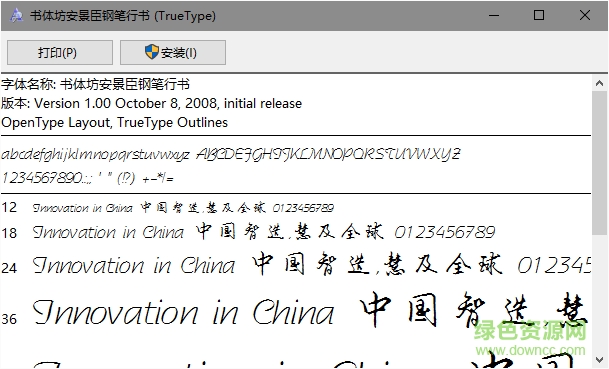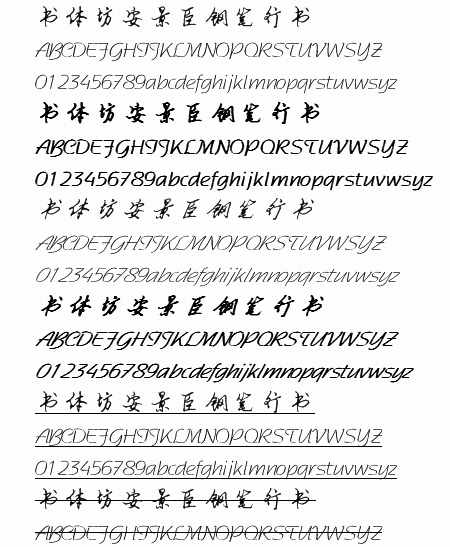
書體坊安景臣鋼筆行書字體是一款俊逸灑脫、筆鋒犀利的鋼筆字體,這款字體有著行云流水般的線條,深受廣大書法愛好者們的喜愛,現(xiàn)在綠色資源網(wǎng)小編為大家?guī)頃w坊安景臣鋼筆行書,感興趣的用戶趕快來免費下載體驗吧!
書體坊安景臣鋼筆行書字體匯聚了鋼筆字體、行書字體的特點,大小相兼。就是每個字呈現(xiàn)大小不同,存在著一個字的筆與筆相連,字與字之間的連帶,既有實連,也有意連,有斷有連,顧盼呼應。